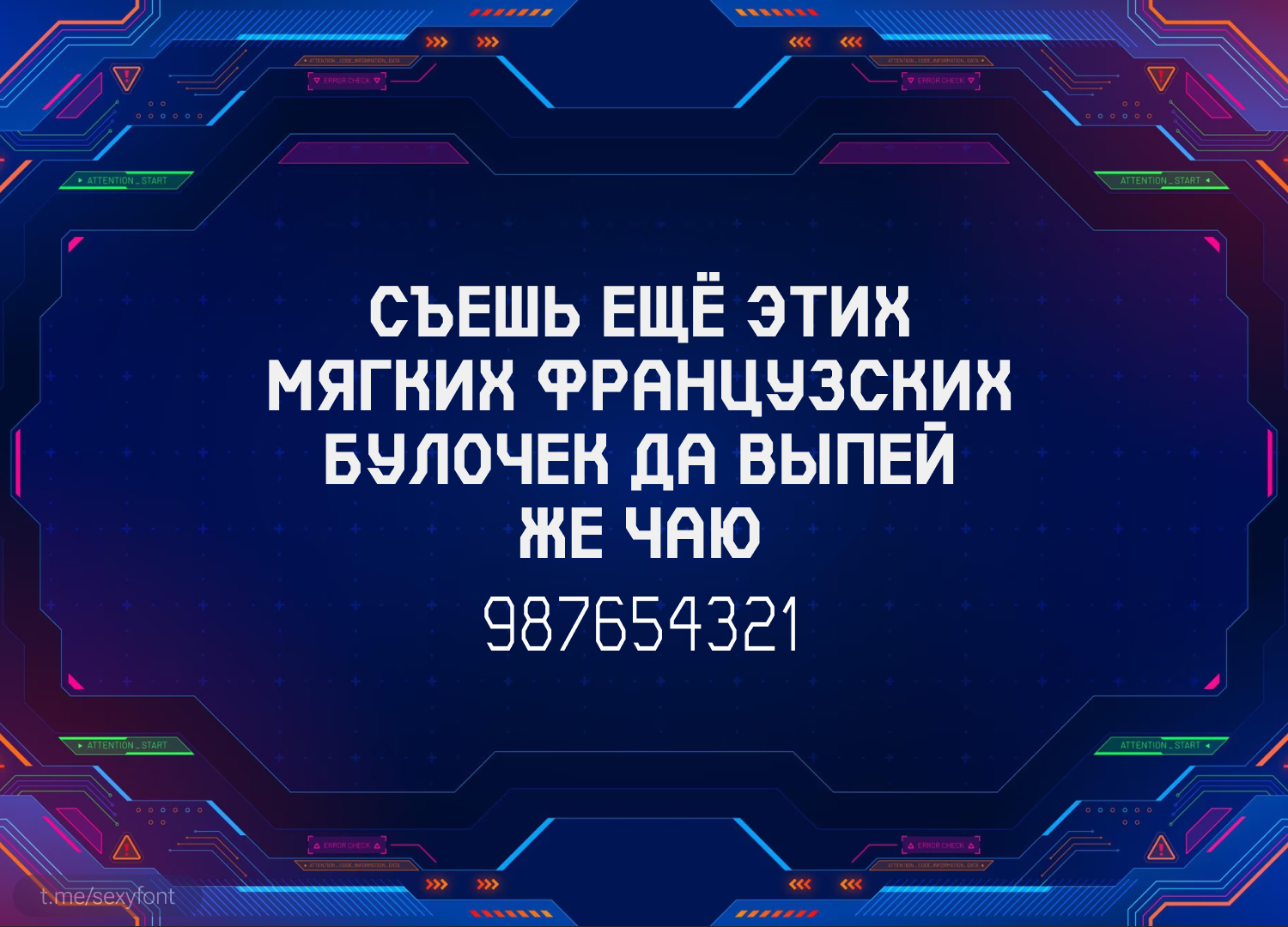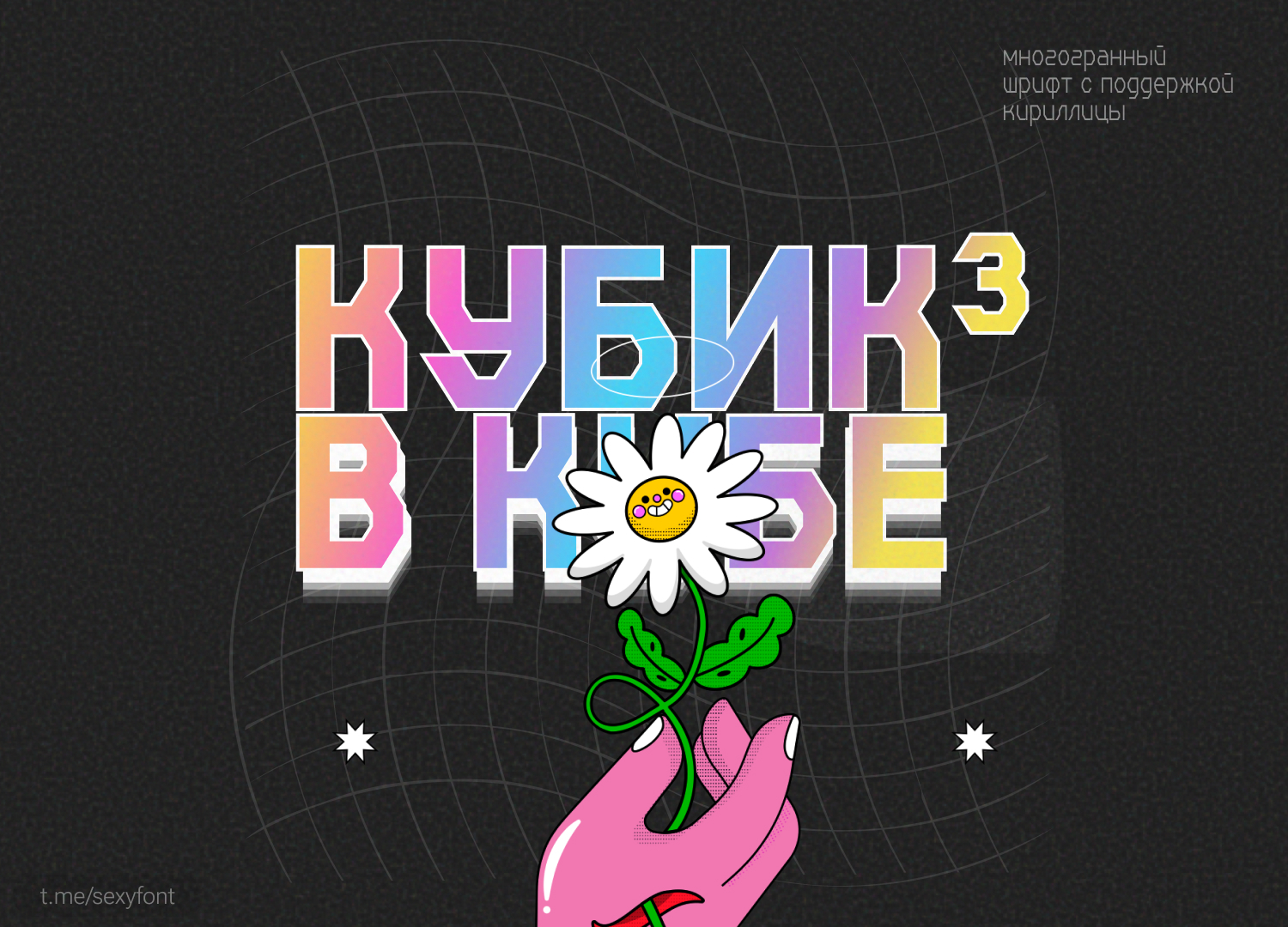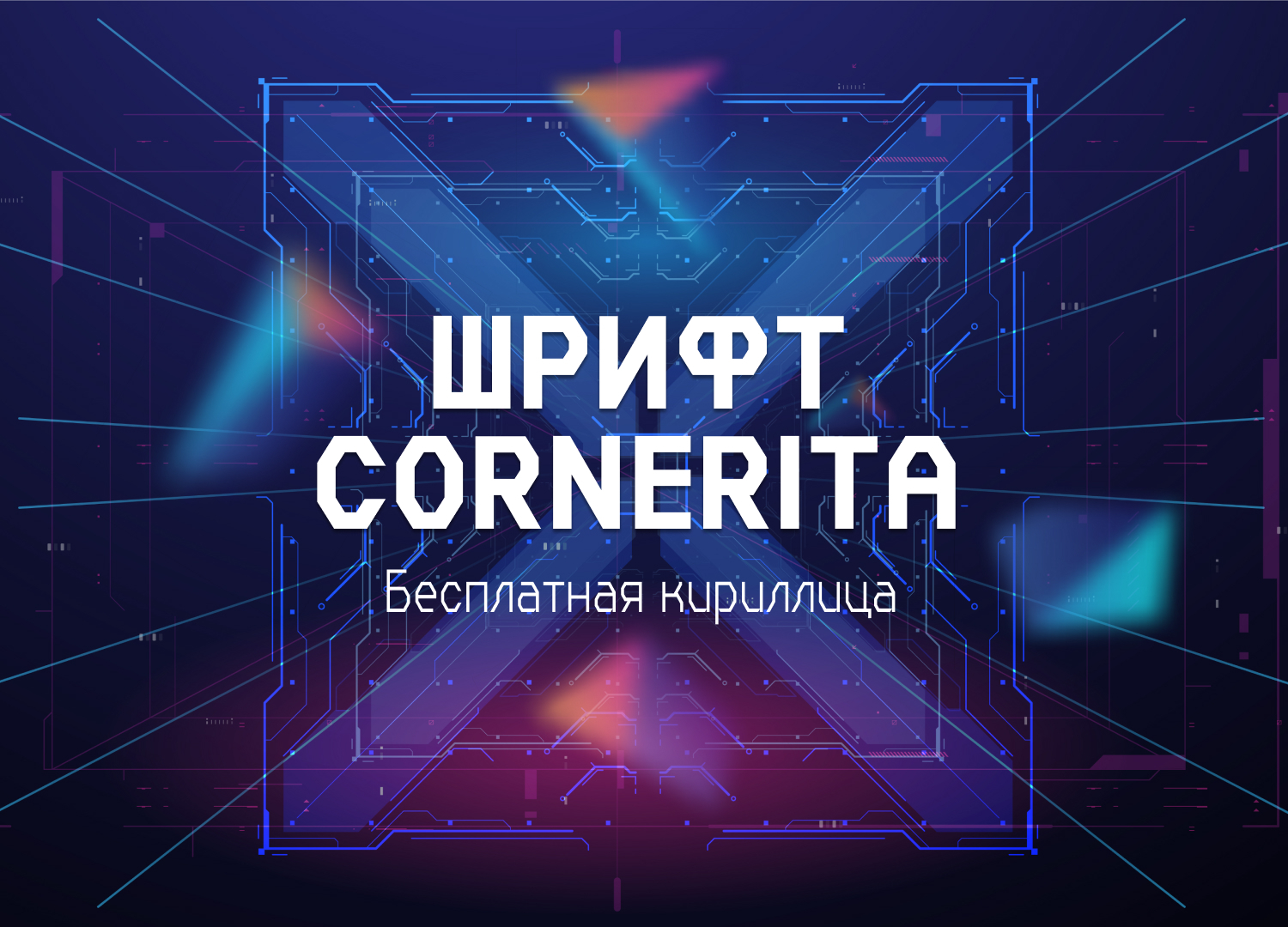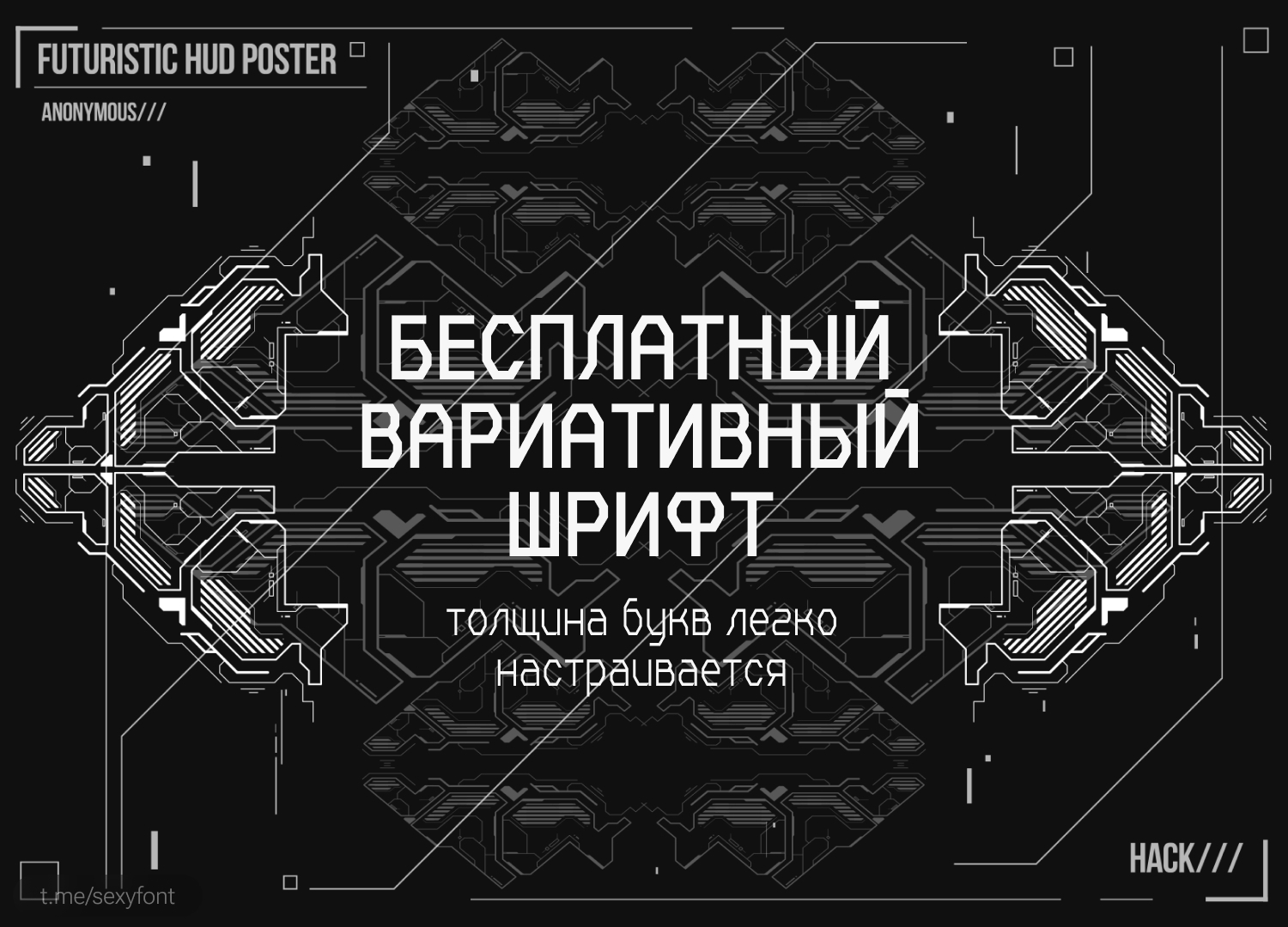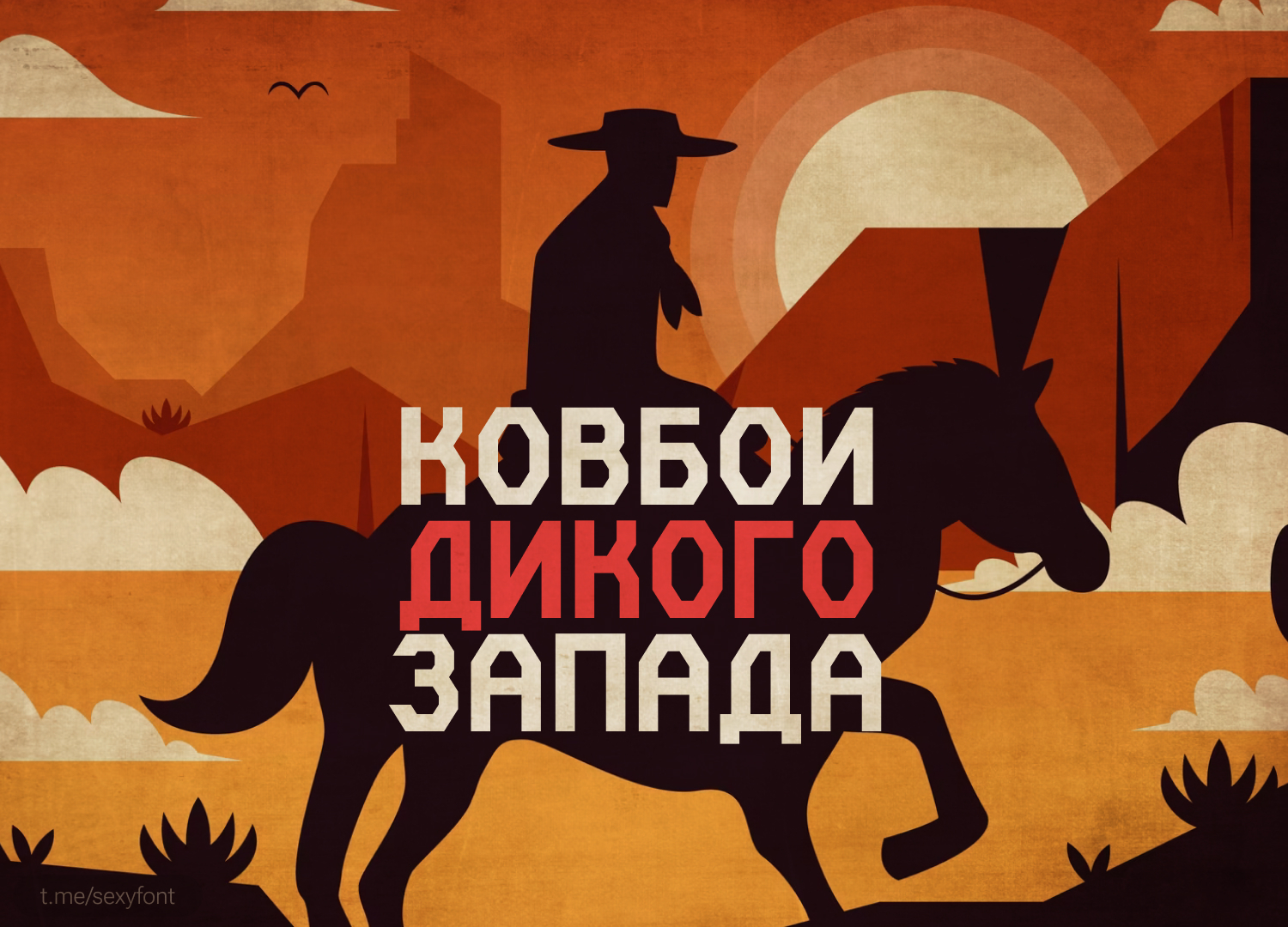
Шрифт Cornerita⁠⁠
Полностью бесплатный шрифт. Буквы имеют форму восьмигранника. Шрифт вариативный, толщину можете настраивать сами) Отлично впишется под футуристичные тематики.